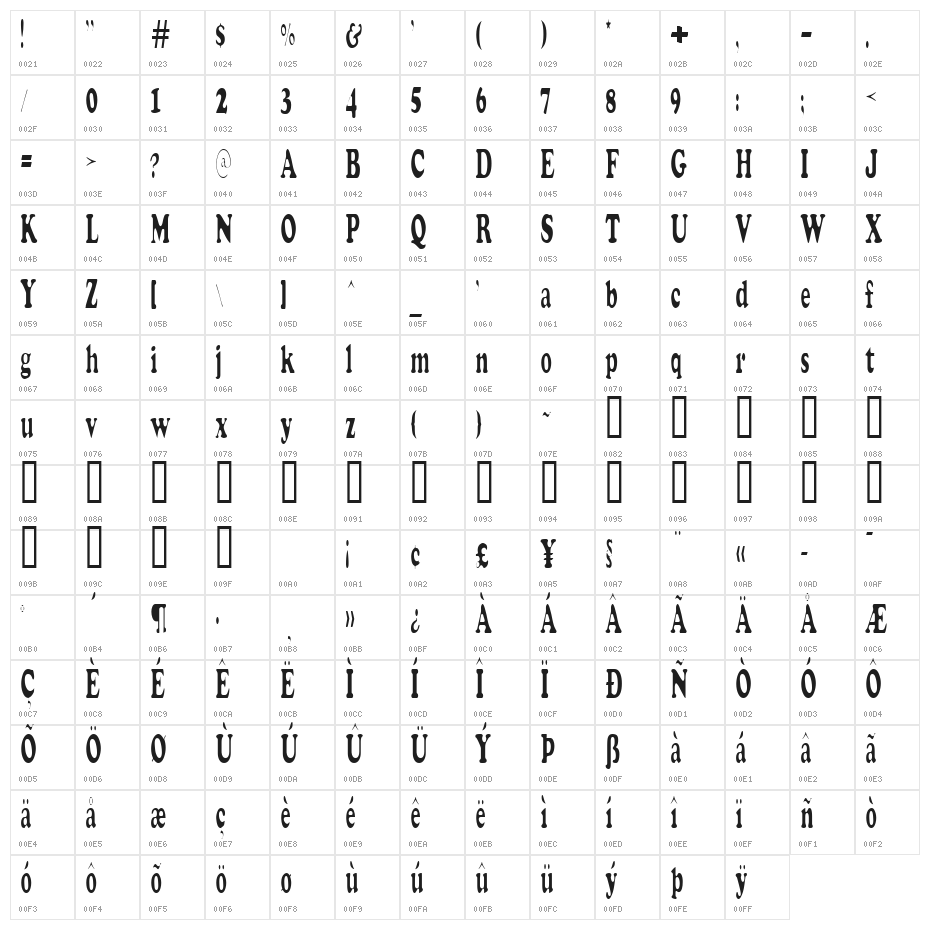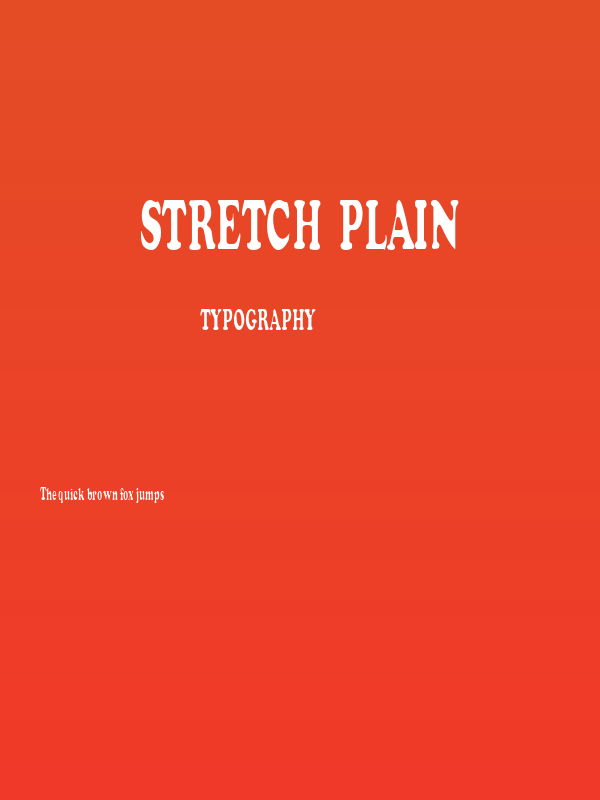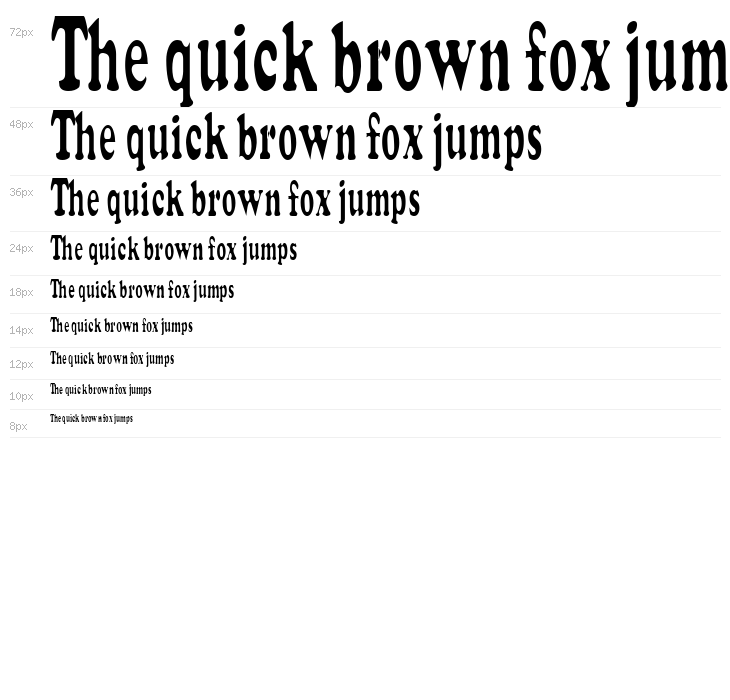
Stretch Plain Font
| العرض | Condensed |
| النمط العام | Playful and bold |
| حالة الاستخدام | Headlines, Posters, Branding |
| مشاريع مقترحة | Ideal for posters, headlines, branding, and any project requiring a bold and distinctive typeface. |